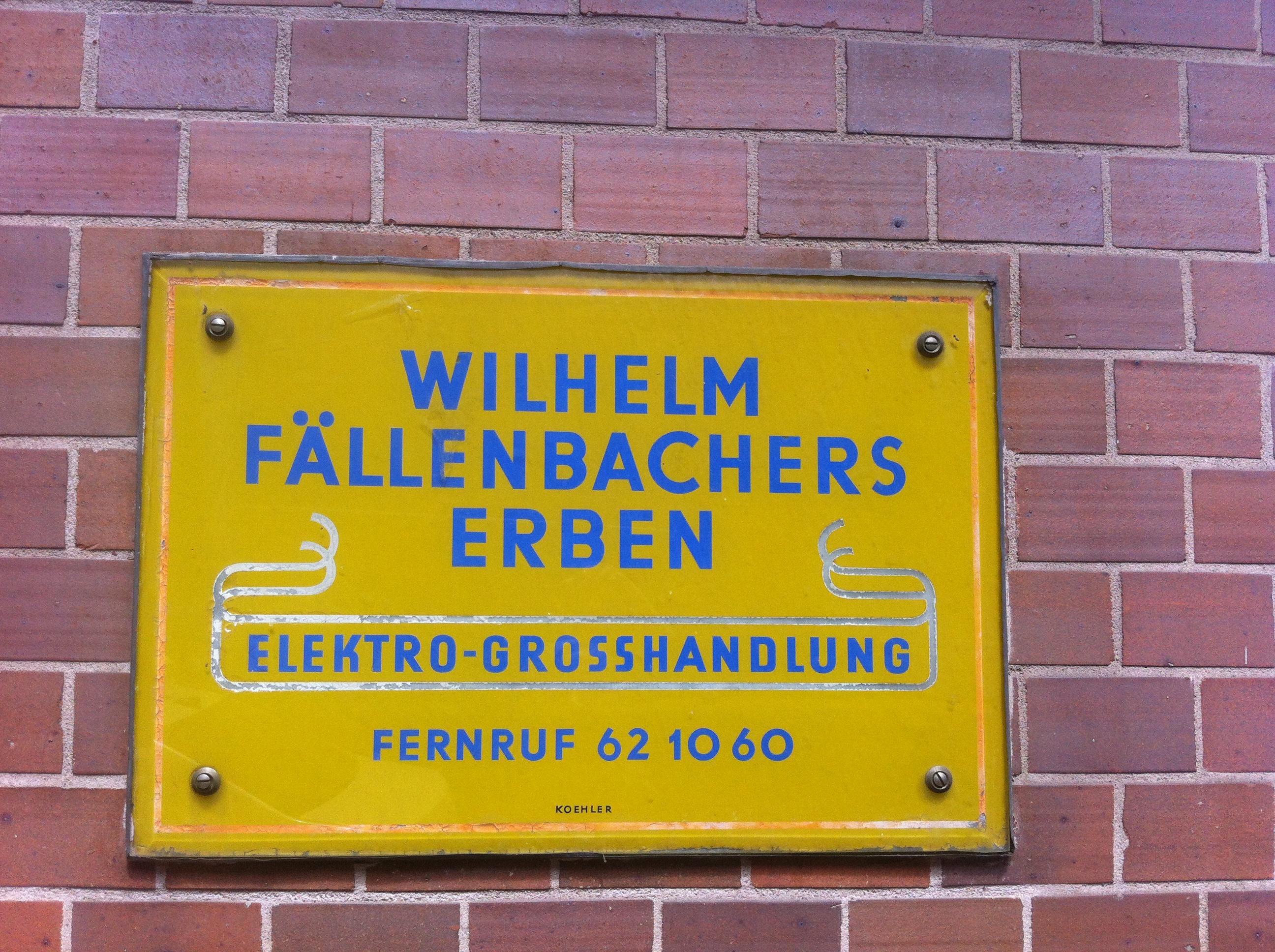
Font identifizieren
Anbei ein Bild zu der gesuchten Schriftart. Kann jemand helfen?
Sind auf dem Bild ggf. mehrere Schnitte verwendet?
Noch nix klrrr, doch vielleicht hilft es, den Schilderhersteller KOEHLER anzufragen, sollte es diesen noch geben.
Mir scheint auch ELEKTRO-GROSSHANDLUNG in anderer als der restlichen Schriftart ausgeführt zu sein.